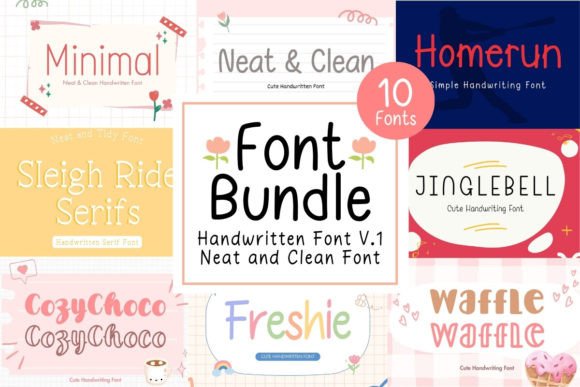
Neat & Clean Handwritten Font Bundle V.1
Die richtigen Designelemente zu finden, kann eine Herausforderung sein, aber Neat & Clean Handwritten Font Bundle V.1 bietet eine außergewöhnliche Sammlung, die Ihre Arbeit sofort aufwertet.
Egal, ob Sie POD-Produkte (Print on Demand), Hochzeitseinladungen oder Social-Media-Grafiken erstellen, Neat & Clean Handwritten Font Bundle V.1 ist die ideale Wahl.